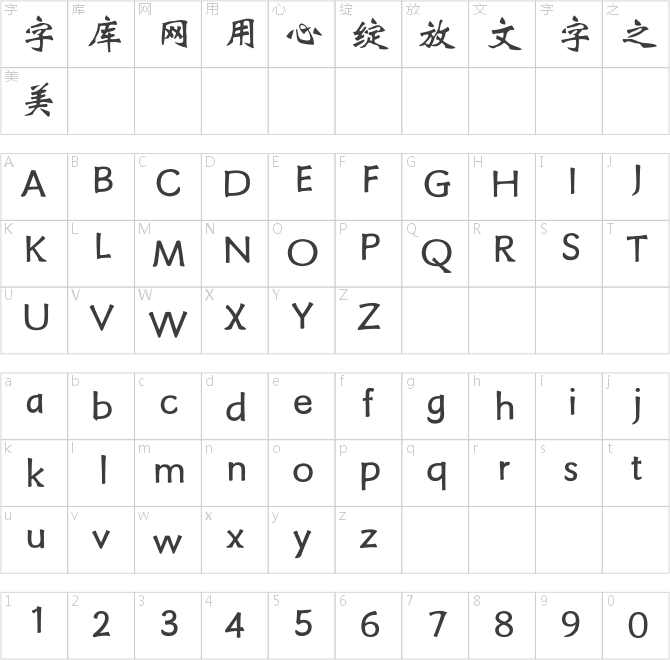
方正魏碑_GBK 詳情頁
字體名稱: 方正魏碑_GB
方正魏碑_GBK
方正魏碑_GBK字體字庫是一款讓人賞心悅目、百看不厭的中文字體,適合各類廣告和產(chǎn)品包裝設(shè)計應(yīng)用,字體大小15.6MB,格式為ttf字體,上傳用戶是g05662,作者/版權(quán)方為方正字庫